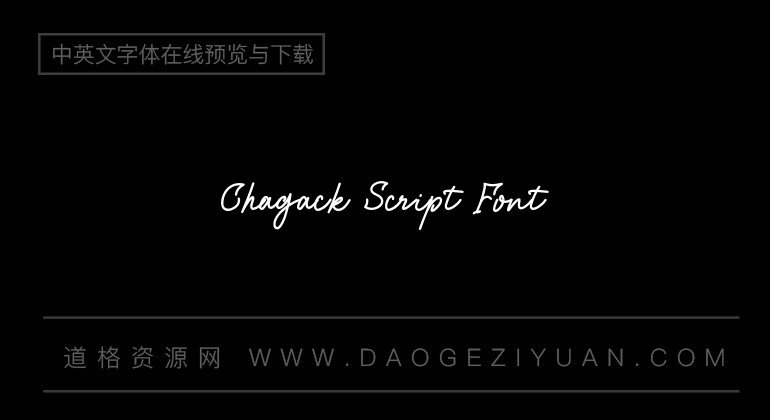
Chagack Script Font
Chagack Script Font 是一款漂亮的手写字体,具有自然且流畅的笔画,适用于各种设计项目,例如印刷品、海报、宣传册、个人品牌等。该字体的特点是大写字母和小写字母有很大的差异,字母之间的连笔也非常自然。此外,该字体还提供了多种字重和风格,可以满足不同设计需求。无论是在标题、标语还是正文中,Chagack Script Font 都能为您的设计增添一份独特和个性化的风格。
Chagack Script Font是一款非常不错的手写艺术字体,具有很好的视觉感,适合于文化类的宣传设计、商业类品牌的广告和产品包装设计以及个性化文字排版等较多场景。